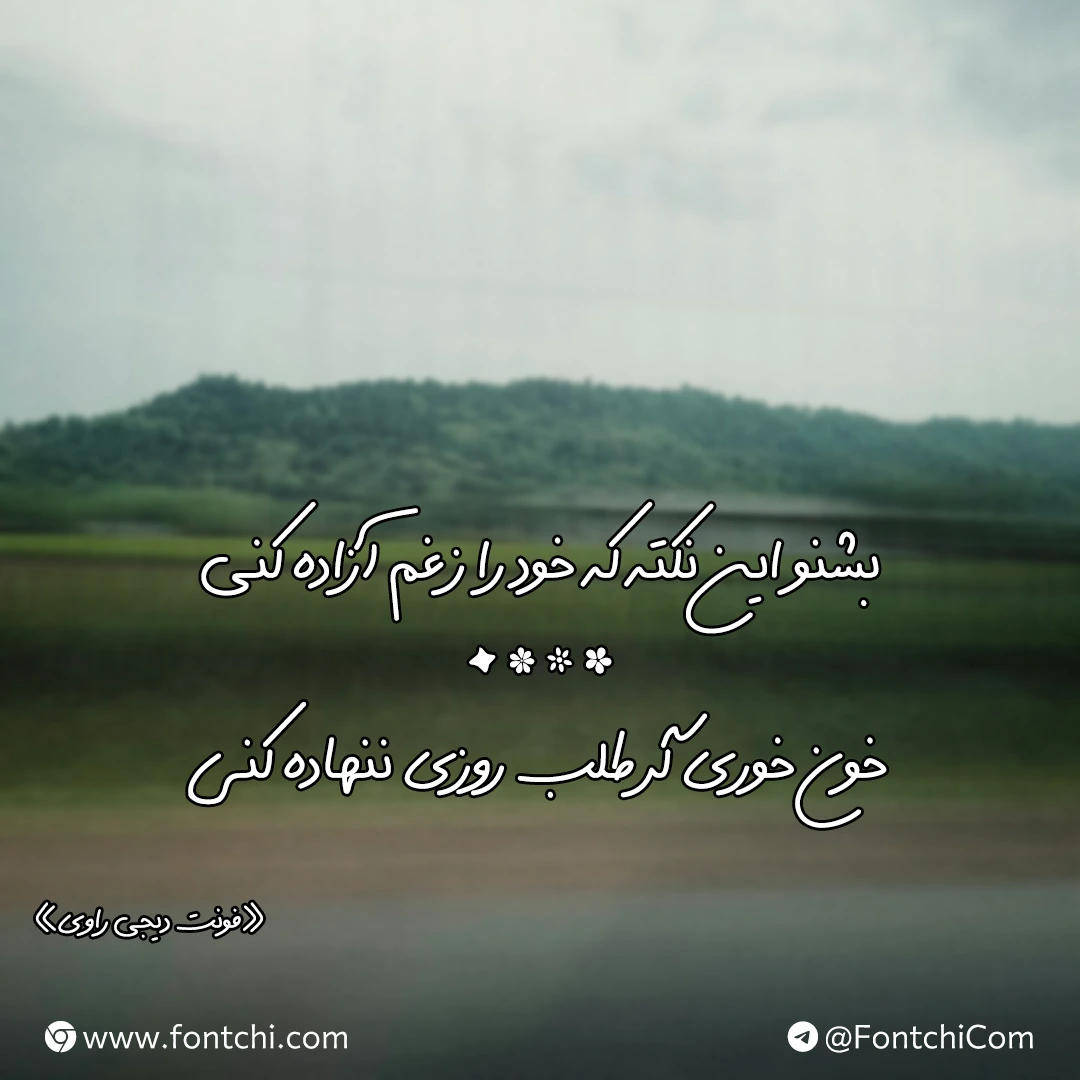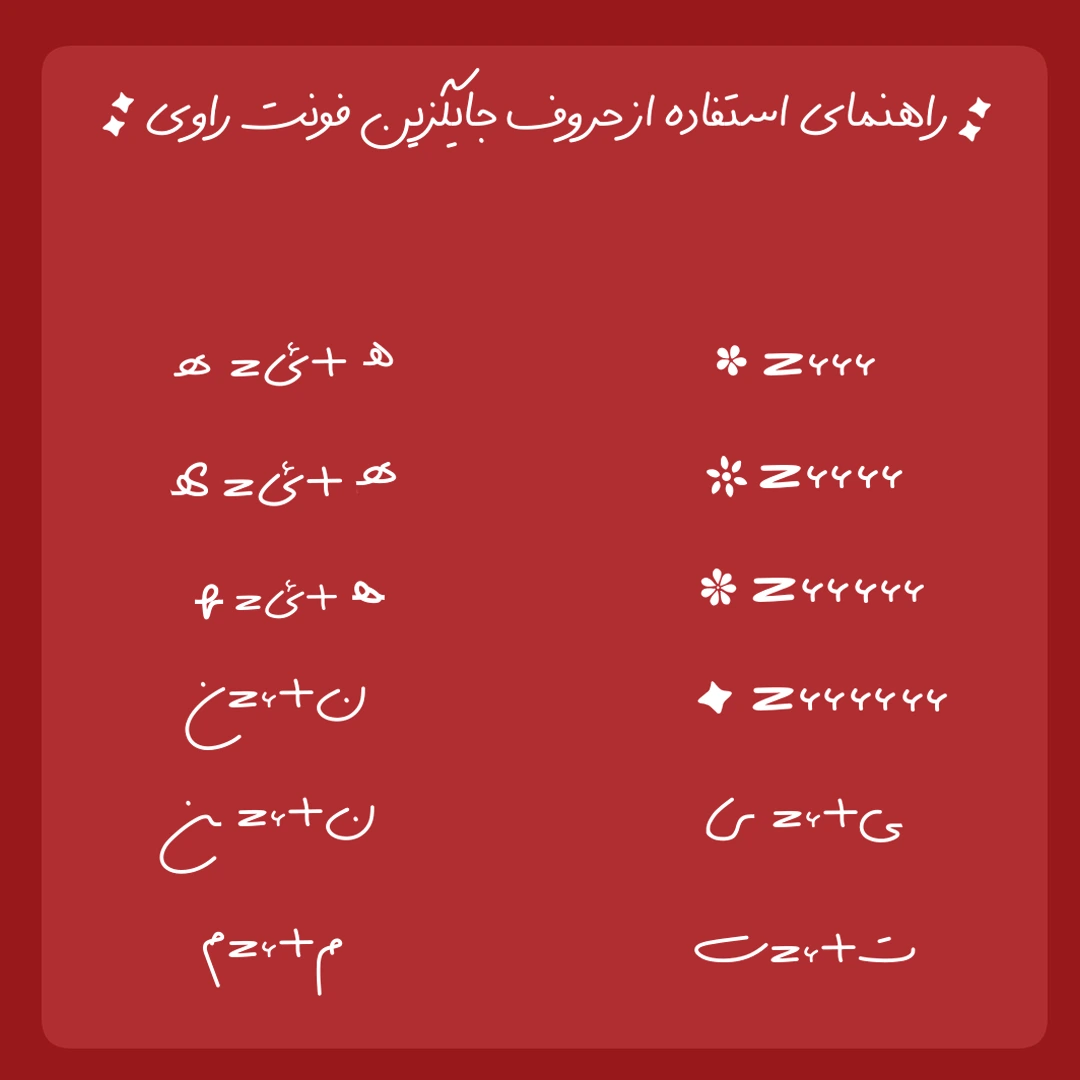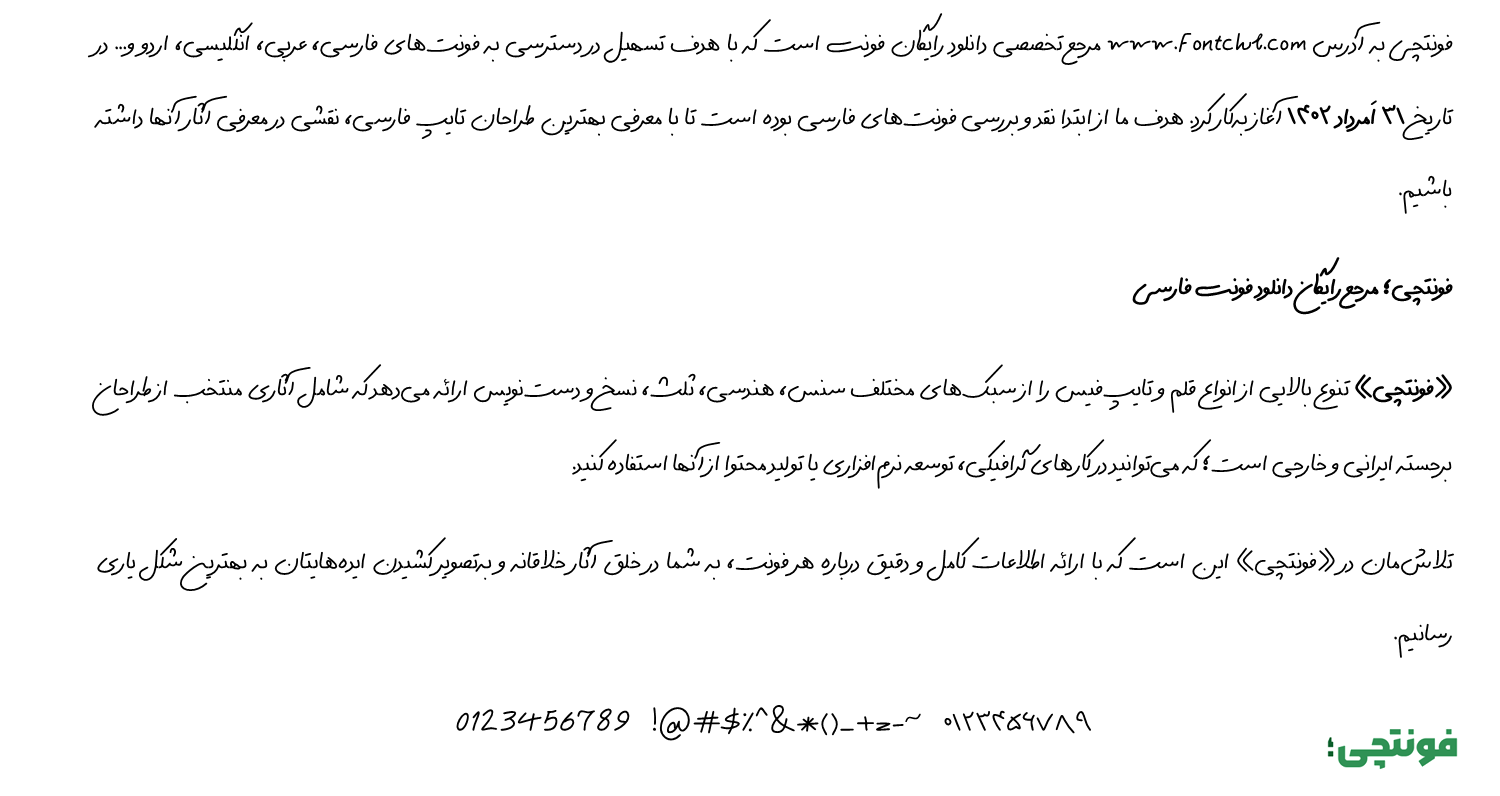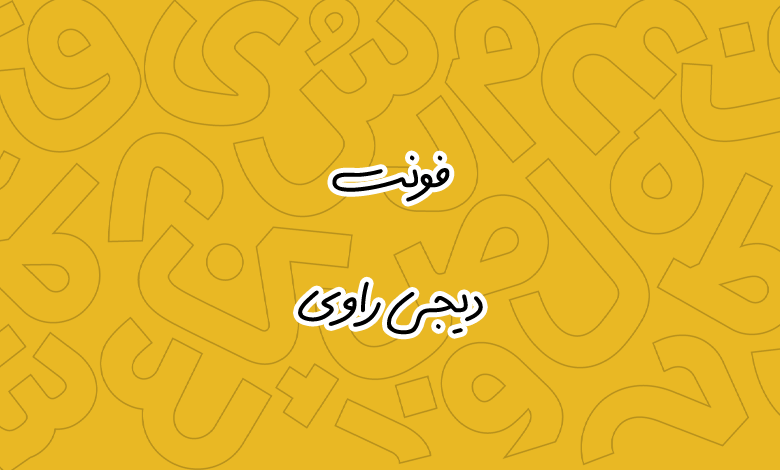
فونت دیجی راوی (Digi Ravi)
فونت دیجی راوی (به انگلیسی: Digi Ravi) از سری فونت‌های دست‌نویس فارسی است که توسط مهدی برقگیر و با همکاری فهیمه نعمت‌الهی طراحی شده است. این فونت با امکاناتی که دارد برای استفاده در دنیای طراحی گرافیک و تولید محتوا، به‌ویژه سات تصاویر عکس نوشته جایگاه ویژه‌ای دارد.
پشتیبانی از چند حرف و ترکیب جایگزین مختلف و همچنین سمبل‌هایی برای زیباسازی متن از جمله ویژگی‌های به‌خصوص این فونت نسبت به سایر فونت‌های سری دیجی هستند. در ادامه به نقد و بررسی کامل این فونت می‌پردازیم.
فونت دیجی راوی با وزن معمولی Regular بر خلاف فونت راوی برای استفاده در متون کوتاه و بیشتر در قالب عکس‌نوشته و شعاری مناسب است. اگر به دنبال فونتی تزئینی برای عکس‌نوشته‌های اینستاگرام یا استوری‌های تلگرامی خود هستید استفاده از این قلم را توصیه می‌کنیم.
این قلم محدود به زبان فارسی نبوده و از سایر زبان‌های کردی و اردو نیز پشتیبانی نسبتا کاملی دارد. همچنین برای زبان انگلیسی نیز سبک خاصی از متن دست‌نویس را پشتیبانی می‌کند که هرچند خیلی نزدیک به نسخه فارسی نیست، اما می‌توانید شما را از فونت لاتین دیگری برای متون چند زبانه بی‌نیاز کند.
کلیه اعراب فونت دیجی راوی دارای کرنینگ متعادلی هستند و با فاصله منظمی در کنار کلمات قرار می‌گیرند. شاید ایرادی که بتوان از این قلم گرفت در بخش اعداد باشد. جایی که برای زبان عربی خبری از اعداد «۰۴۵۶» نبوده و از همان اعداد فارسی «۰۴۵۶» استفاده شده است.
دیجی راوی؛ یک راوی قصه‌گوست که با قلمش به‌جای صدا، با خطوط نرم و روانش داستان می‌گوید. این فونت، مثل یک دوست صمیمی و پراحساس، با دست‌خطی گرم و عاشقانه وارد دنیای طراحی شما می‌شود. اگر بخواهیم دیجی راوی را در یک کلمه توصیف کنیم، آن کلمه «شاعرانه» است. خطوطش مثل شعری روان و ملایم، گاهی بازیگوش و گاهی عمیق، در هر طرحی که استفاده شود، حس و حال خاصی را منتقل می‌کند.
از طراحی پوسترهای تبلیغاتی دوستانه گرفته تا تولید محتوای اینستاگرام، استوری و حتی لوگوتایپ‌های خلاقانه، این فونت می‌تواند جادوی خودش را به کار ببرد. برای نوشتن یک نقل‌قول عاشقانه روی تصویر یا یک کاور اینستاگرامی که نگاه‌ها را بدزدد، دیجی راوی می‌تواند در اولویت‌های شما باشد.
راهنمای استفاده از حروف جایگزین فونت دیجی راوی
یکی از امکانات قلم دیجی راوی وجود حروف جایگزین و سمبل‌هایی که با کلیدهای ترکیبی است که اجازه می‌دهد متون خود را بدون نیاز به انجام کارهای پیچیده طراحی در برنامه‌هایی مثل فتوشاپ و ایلاستریتور، با خلاقیت بیشتری بنویسید.
مطابق تصویر بالا می‌توانید برخی حروف فارسی و عربی را با افزودن کاراکترهای «ء، ئ» به انتها یا میانه برخی حروف، با ظاهری متفاوت‌تر تایپ کنید. همچنین با تایپ کاراکتر «ء» از تعداد ۳ تا ۶ عدد پشت سر هم می‌توانید چند سنبل را تایپ کنید که برای متون عکس نوشته یا شعر بسیار کاربردی هستند.